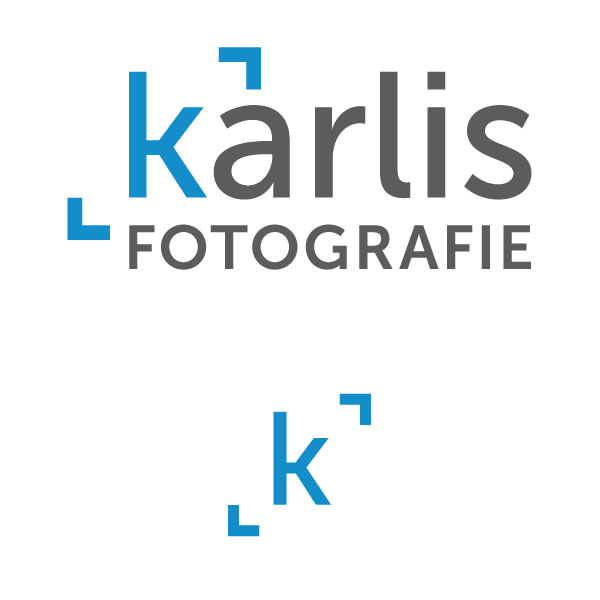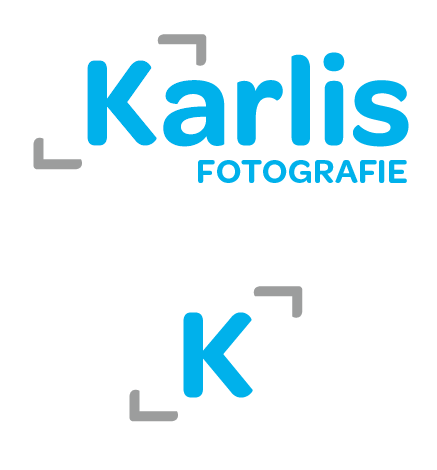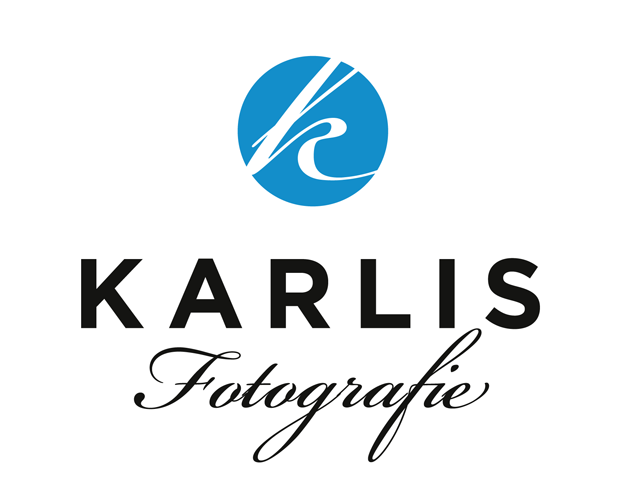
Meinung zum Logo gefragt und Schriftalternativen gesucht!
für meine fotografischen Tätigkeiten bin ich gerade dabei ein Corporate Design bzw. ein Logo anzufertigen. Aus mehreren Entwürfen habe ich mich nun (fast) für das untere entschieden aber irgendwie fehlt mir noch der "Kick", wenn ihr wisst was ich meine. Was ich letztendlich möchte, ist ein vielseitig verwendbares Logo, d.h. dass man einen Teil nur als Signet verwenden kann. In diesem Falle wäre es das "k" mit den Ecken... Kurz vielleicht noch was zum Tätigkeitsbereich bzw. der Zielgruppe: Es geht um die Hochzeitsfotografie/Hochzeitsreportage. Da möchte ich auf jeden Fall hin. Die Zielgruppe ist daher eher weiblich ausgerichtet... Gleichzeitig möchte ich aber vermeiden, das Logo auf absichtlich "festlich" zu trimmen.
Nun, ich bin gespannt auf eure Meinungen dazu!
PS: Momentan verwende ich die Schrift "Museo Sans".
hier eine erste unqualifizierte Meinung :-)
die Idee mit den blauen Ecken gefällt mir gut und lässt mich gleich an einen Fotografen denken, der seine Hände aufspannt um ein Motiv zu suchen. Was mir nicht gefällt ist die Umsetzung im Logo … Zum einen sollten die Ecken asymmetrisch sein, weil bei den Händen ja auch ein Teil länger ist.
Außerdem überzeugt mich die Integration in den Schriftzug nicht. spricht was dagegen, den ganzen Schriftzug mit den Ecken einzurahmen und nicht nur das K? Die obere Ecke hängt so damoklesmäßig über dem a, ich würde die versuchshalber mal nach ganz rechts schieben. Die untere Ecke kollidiert noch etwas mit der „Fotografie“-Zeile, aber ich weiß grad nicht was man damit tun kann. Insgesamt fehlt mir auch ein Bisschen Dynamik im Logo.
Die Marke mit dem einzelnen K finde ich ganz gut aber auch zu symmetrisch, hier würde ich die Ecken (wie oben) auch asymmetrisch gestalten und ein Rechteck statt eines Quadrates aufziehen. Das Rechteck sollte breiter als hoch sein, das entspricht dann zwar nicht der Form des Ks aber zeichnet sich vor meinem geistigen Auge ganz nett ab :-)
Drei kurze Gedanken, die mir spontan einfielen:
1. Das k wirkt nicht richtig zentriert, da es im oberen rechten Quadranten sozusagen eben diesen Weißraum hat. Mit einem Versal K würde das wohl besser funktionieren.
2. Ich finde den Namen mit der Unterzeile zu blockig, da fehlt die Dynamik. Vielleicht mal mit den Schriftgrößen herumprobieren oder die Unterzeile erweitern, so dass sie unter dem Namen rechts raus ragt.
3. Diese ›Sucherecken‹ bei Fotografenlogos sieht man natürlich oft. Ich finde sie aber nicht schlecht umgesetzt und eingebaut (bis auf das k, wie gesagt)
… Zum einen sollten die Ecken asymmetrisch sein, weil bei den Händen ja auch ein Teil länger ist.
... und das klassische Fotoformat ist ja auch nicht quadratisch :-)
(Das war mir jetzt beim ersten schnellen Drüberschauen nicht aufgefallen)
Ich finde es zu voll, zu gedrängt und zu viele Dinge auf einmal ein ein Logo gepackt.
Die "Buchstabenmarke" finde ich eine gute Idee, allerdings halte ich es da mit den Schnitzelschen Ausführungen: ein versales K wäre besser. Zudem kippt die Marke wenn sie allein steht. Für eine vernünftige Verbindung mit dem kompletten Namen würde ich diesen nicht einfach an die Marke drankleben.
Mir ist das Ganze auch zu vollgepackt; versuche doch mal, die Unterzeile ganz wegzulassen.
Vielen Dank für die bisherigen Meinungen! Die genannten Punkte und Sichtweisen kann ich von euch absolut nachvollziehen. Vielleicht sollte ich noch Mal auf "reset" drücken und von vorne beginnen… für mich könnte oder müsste sogar, das Logo ein bisschen femininer wirken… vielleicht also als Grundform was rundes, weibliches nehmen… hmmm… Gar nicht so einfach, wenn die eigenen Ansprüche so hoch sind. :-)
Ich finde es zu voll, zu gedrängt und zu viele Dinge auf einmal ein ein Logo gepackt.
dem schließe ich mich an. ich würde mit den schriftgrößen nochmal herumspielen und ggf. mal schauen wie es aussieht wenn das wort fotografie beim a anfängt. 4:3 anstelle des quadratischen formates würde ich ebenfalls bevorzugen.
zum thema 'femininer' ...
ich persönlich würde jetzt keine hochzeitsfotografie mit dem logo in verbindung bringen, jedoch
find ich das auch nicht schlimm. es sei denn du tritts wirklich und ausschließlich als hochzeitsfotograf
auf, aber selbst da ... hmm. nö – muss nicht. da kann man dann auch bei der restlichen gestaltung
darauf achten. vielleicht mal eine 'weichere' schrift, eine rounded oder eine 'finger sans' probieren.
die ecken könnte man dann ebenfalls in diesem style probieren.
finger sans
https://www.myfonts.com/fonts/fontfont/strada
rounded
https://www.myfonts.com/fonts/dstype/estilo-text/
ich würde die Ecke sogar ganz nach rechts ziehen … Das K alleingestellt kippt aber immer noch.
Meinem statischen Empfinden widerstrebt es, daß die luftige Schreibzeile unter der schweren Groteskzeile hängt und von dieser quasi erdrückt wird. Das fände ich umgekehrt besser.
Das hätte ich beinahe blind unterschrieben. Aber als ich mir das Logo dann noch einmal angesehen habe, hat sich das dann doch nicht bestätigt. Für mich hält die »schwere Groteskzeile« in der Mitte das alles stabil zusammen und die »luftige Schreibzeile« hängt ganz locker, unangestrengt und unbedrängt darunter.